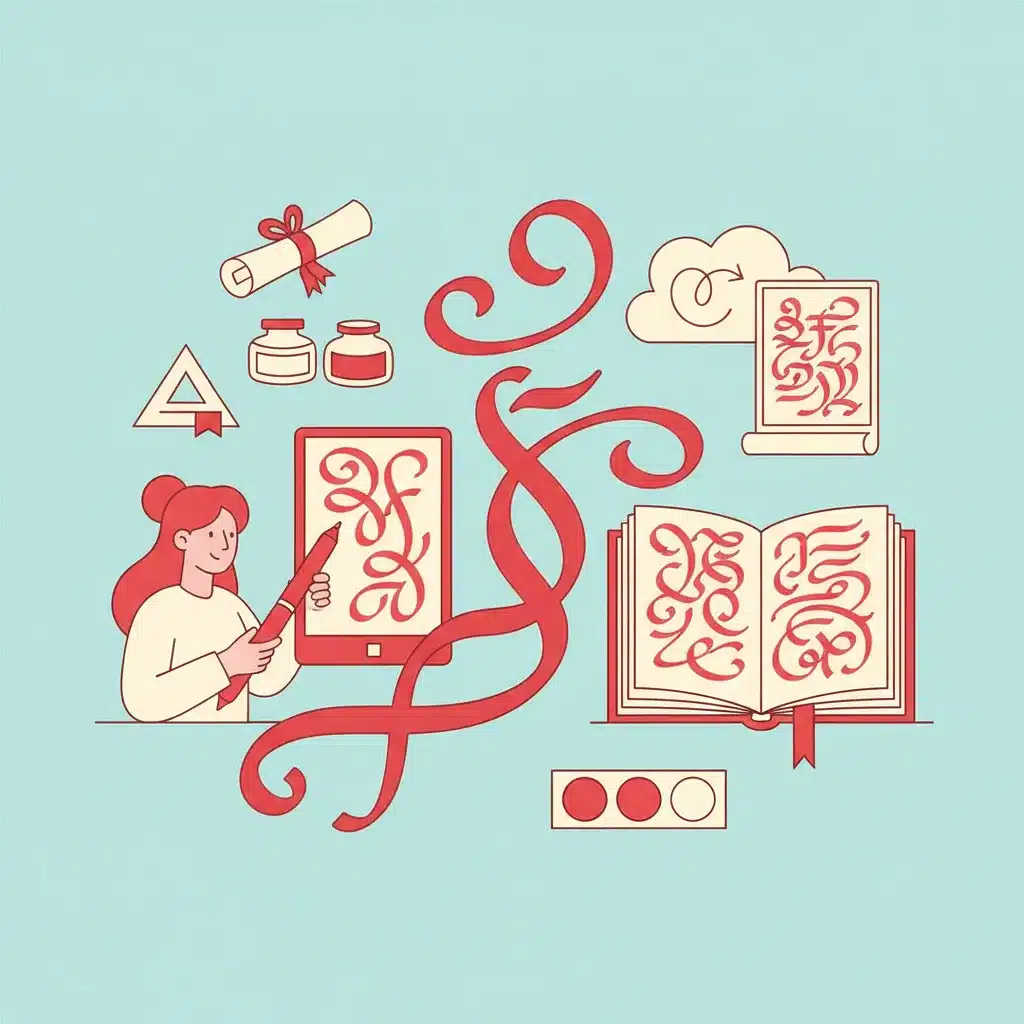
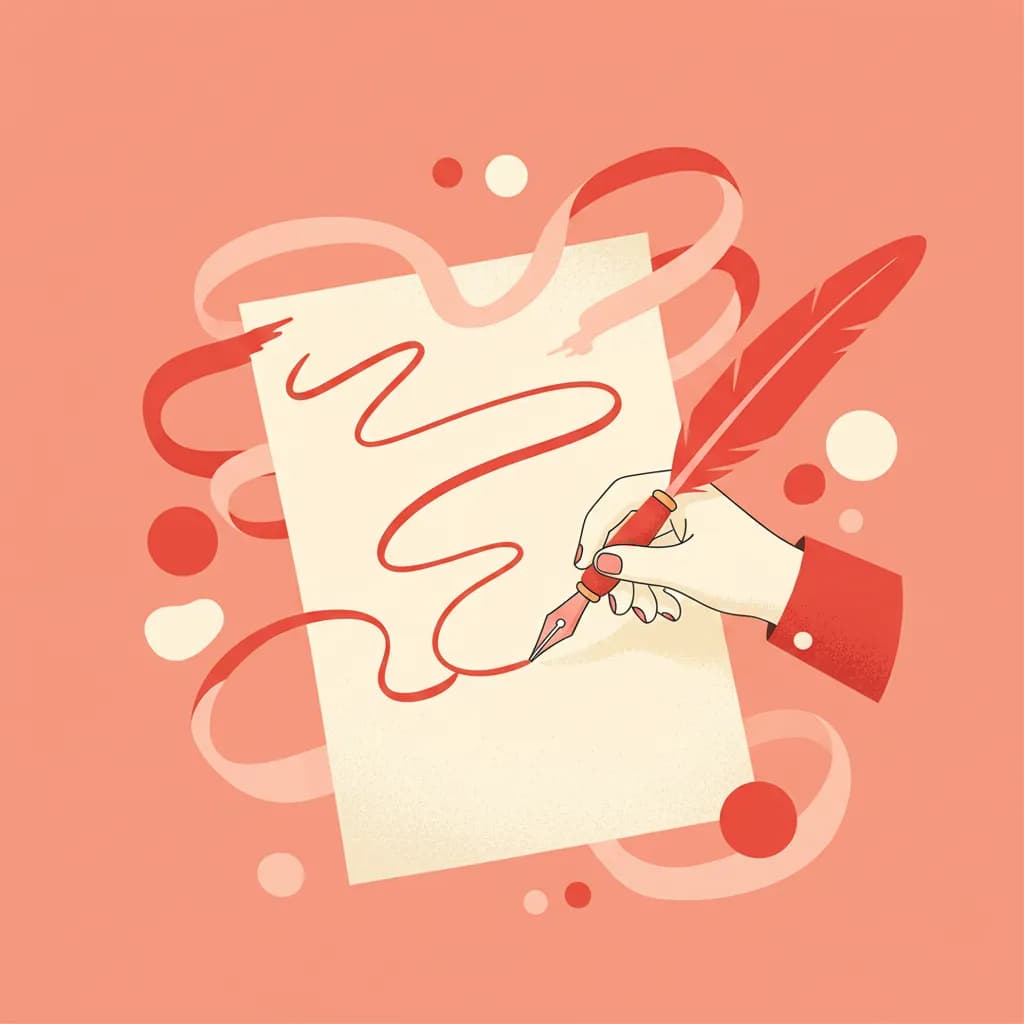
כשמעצב מוסר עיצוב ללקוח ומקבל בחזרה את התגובה "זה נראה כמו כולם" – הסיבה לרוב אינה הצבעים ואינה הפריסה. הסיבה היא הפונט. גופנים כתב יד הם הכלי הטיפוגרפי החזק ביותר ליצירת זהות ויזואלית שמרגישה אנושית, חמה ובלתי נשכחת. בין אם מדובר בזימון חתונה, מיתוג עסקי, עיצוב אריזה או פוסט ברשת החברתית – הבחירה הנכונה בגופנים כתב יד יכולה לשנות את הרושם הכולל באופן דרמטי.
⚡ נקודות מפתח:גופנים כתב יד הם פונטים שמדמים את תנועת היד האנושית בכתיבה – בין אם מדובר בקליגרפיה מדויקת, בכתב יומן אישי או בעט מברשת אקספרסיבי. מה שמייחד אותם מכל שאר הפונטים הוא היכולת להעביר רגש בצורה מיידית. כשהצופה רואה כתב יד – גם כשהוא דיגיטלי – המוח מקשר אותו אוטומטית לאדם שמחזיק עט, לכוונה אישית, לחום של קשר אנושי.
בתחום הפונטים בעברית, אתגר הכתב יד הוא כפול: אותיות עבריות מורכבות יותר מבחינה גרפית, ולכן עיצוב פונט כתב יד עברי שנראה טבעי ובו-זמנית קריא דורש מיומנות גבוהה במיוחד. הפתרונות הטובים ביותר הם אלה שנבנו ישירות מכתב ידם של אנשים אמיתיים, ועברו תהליך דיגיטציה קפדני.
לפי עקרונות ה-UX Research, טיפוגרפיה שמדמה כתב יד מגבירה את תחושת האמון והאותנטיות של המסר. זו הסיבה שמותגים בתחום האוכל, האירועים, הטיפוח והיצירה נוטים לבחור בגופנים כתב יד כחלק ממערכת המיתוג שלהם.
הבחירה בגופנים כתב יד אינה עניין של טעם בלבד – היא החלטה אסטרטגית שמשפיעה על האופן שבו הקהל קולט את המסר. כל פונט כתב יד נושא אופי משלו, ויש להתאים אותו לסוג הפרויקט ולקהל היעד.
לדוגמה, לעיצוב הזמנות לחתונה שמחפשת אווירה חגיגית ורומנטית, פונט לאבלי הוא דוגמה לפונט כתב יד דומיננטי שעוצב עם עט מברשת ומעניק תחושה של יוקרה ורגש. לעומתו, לפרויקט שובב ואנרגטי יותר, פונט רולינג – שעוצב בעזרת rolling pen – מביא אנרגיה שונה לחלוטין.
תהליך הבחירה ב-4 שלבים:
שלב 1: הגדירו את האופי הרצוי
האם הפרויקט דורש חגיגיות, חמימות, שובבות או יוקרה? כל תשובה מובילה לתת-קטגוריה שונה של גופנים כתב יד.
שלב 2: בדקו קריאות בגדלים שונים
הדפיסו או הציגו את הפונט ב-12pt, 24pt ו-48pt. גופנים כתב יד שנראים מדהימים בגדול עלולים להיות בלתי קריאים בגדלים קטנים.
שלב 3: בחנו את ההרמוניה עם הפונט המשני
פונט כתב יד עובד בצמד עם פונט "עגון" – sans-serif קריא שמאזן את האקספרסיביות. ניגוד בין הדינמי לסטטי יוצר היררכיה ויזואלית ברורה.
הבחירה בפונט כתב יד יפה אינה מספיקה – השימוש בו חייב להיות מושכל. אחת הטעויות הנפוצות ביותר היא שימוש בגופנים כתב יד לטקסט גוף ארוך. פונטים מסוג זה מתאימים לכותרות, לציטוטים בולטים ולאלמנטים דקורטיביים – לא לפסקאות של עשרות מילים.
טעות נוספת היא שימוש בשני גופנים כתב יד שונים באותו עיצוב. שני פונטים אקספרסיביים יוצרים "רעש ויזואלי" שמקשה על הקורא למצוא היררכיה ברורה. הכלל הוא: פונט כתב יד אחד, פונט "עגון" אחד – וזהו. לקריאה נוספת על גופנים עבריים שמשדרגים כל עיצוב – מומלץ לבדוק את האוסף המלא.
טעות שלישית היא התעלמות מהמקור האנושי של הפונט. גופנים כתב יד שנבנו מכתב ידם של אנשים אמיתיים – כמו פונט שחר הדר שנבנה מכתב ידה של משוררת, או פונט אניטה שמרגיש כמו כתב יד ביתי חמים – נושאים אופי עמוק יותר מאשר פונטים שעוצבו בצורה מלאכותית.
בתחום הטיפוגרפיה הדיגיטלית, ממליצים מומחים להגביל את השימוש בפונט כתב יד לאלמנטים שאינם עולים על 20% מסך הטקסט בעיצוב. כך הפונט שומר על כוחו ולא הופך לרעשני.
עקרונות הפעולה הבאים יעזרו לכם להפיק את המרב מגופנים כתב יד בכל פרויקט, בין אם דיגיטלי ובין אם מודפס:
לפרויקטים של עיצוב אריזה או הדפסה, שווה לבדוק את פונט אופטימיסט – פונט כתב יד חינני שזמין במשקלים שונים (קל, רגיל, בולט, כבד) ומאפשר גמישות עיצובית רבה. בתחום הטיפוגרפיה למדיה מודפסת, הגמישות של משקלים מרובים היא יתרון משמעותי.
לחקור את הפונטים ←כן, אך עם זהירות. גופנים כתב יד עובדים מצוין בלוגואים כאשר הם ייחודיים, קריאים בגדלים קטנים ומשקפים את אופי המותג. חשוב לבדוק שהפונט נראה טוב גם בשחור-לבן וגם בגדלים זעירים כמו על כרטיס ביקור.
פונט קליגרפי מבוסס על טכניקות כתיבה מסורתיות עם עט נובע או עט מברשת – הוא מאופיין בשינויי עובי קו דרמטיים ובדיוק גבוה. פונט כתב יד "רגיל" מדמה כתיבה יומיומית אנושית, עם חוסר סימטריה מכוון שנותן לו תחושת אותנטיות. שניהם שייכים לקטגוריית גופנים כתב יד, אך מתאימים לפרויקטים שונים.
גופנים כתב יד הם הגשר בין הדיגיטלי לאנושי. הם מזכירים לצופה שמאחורי כל מסר עיצובי עומד אדם עם כוונה, עם רגש ועם סיפור לספר. בעולם שבו כל עיצוב נוצר בכלים דיגיטליים, הבחירה בפונט שמדמה כתב יד היא אקט של בידול – דרך לומר "זה לא עוד תבנית, זה נעשה בשבילך."
הצעד הבא הוא פשוט: בחרו פרויקט אחד שעומד לפניכם – הזמנה, פוסט, כרטיס ביקור – ונסו להחליף את פונט הכותרת בגופן כתב יד שמתאים לאופי שלו. התוצאה, לרוב, מדברת בעד עצמה.
רעיונות ליישום מיידי: